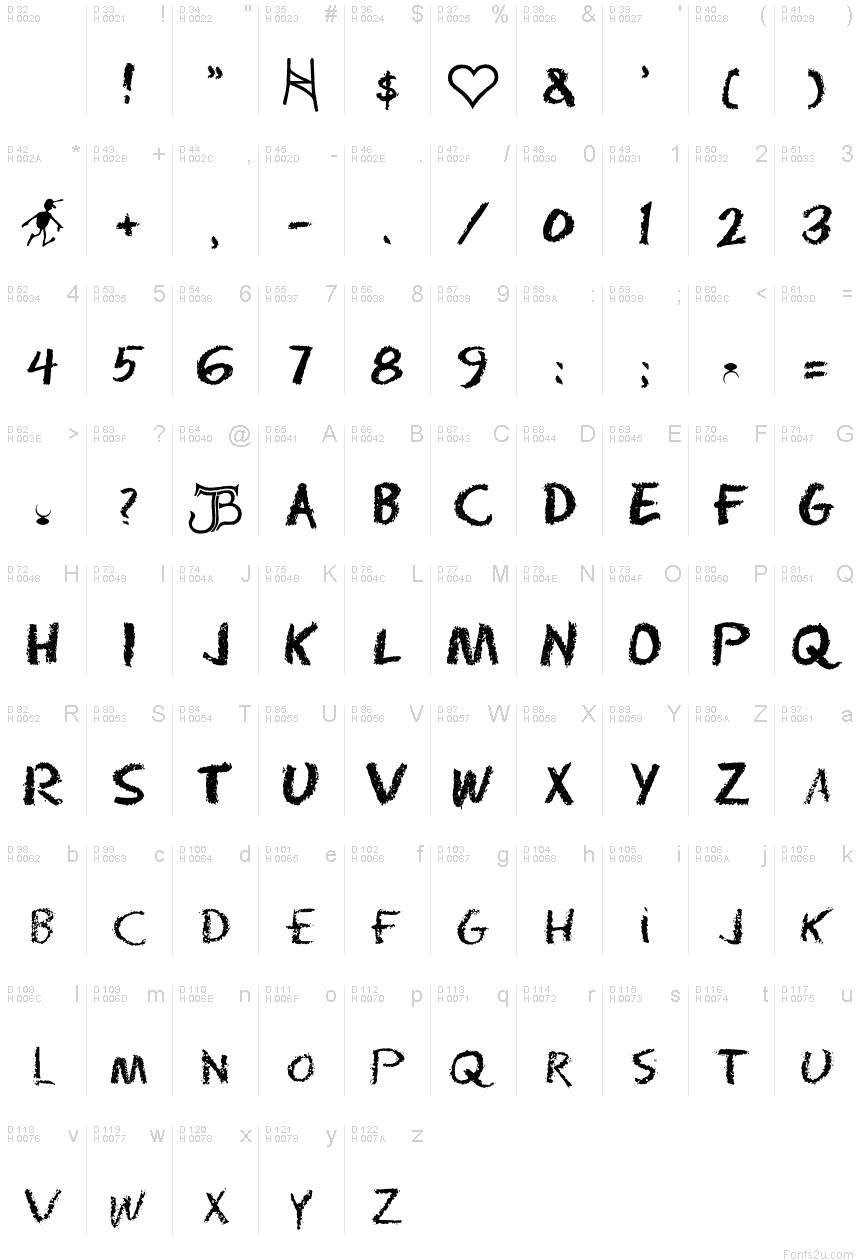
Radium Day-After J autorstwa InFerNo to darmowy krój pisma typu "trash script" z rodziny Radium J, który wygląda, jakby został przeciągnięty przez kwas, żwir i szum statyczny. Litery sprawiają wrażenie nadpalonych i ochlapanych, z szorstkimi, nieregularnymi krawędziami, które nadają każdemu słowu szaleńczą, apokaliptyczną energię. Jest chaotycznie, ale wciąż czytelnie, więc zyskujesz cały ten brud i napięcie, nie tracąc przy tym przekazu.
Używając Radium Day-After J, wprowadzisz plakaty horrorów, okładki albumów metalowych czy punkowych, tytuły gier z efektem glitch, ulotki na Halloween, zin i mroczne miniatury na YouTube w tryb pełnego chaosu. Ten darmowy font najlepiej sprawdza się w dużym rozmiarze, gdzie nakrapiana tekstura może naprawdę „pełznąć” po stronie. Do tekstów uzupełniających dobierz prosty, wąski bezszeryfowy krój, aby utrzymać chaos w ryzach i zachować równowagę projektu.